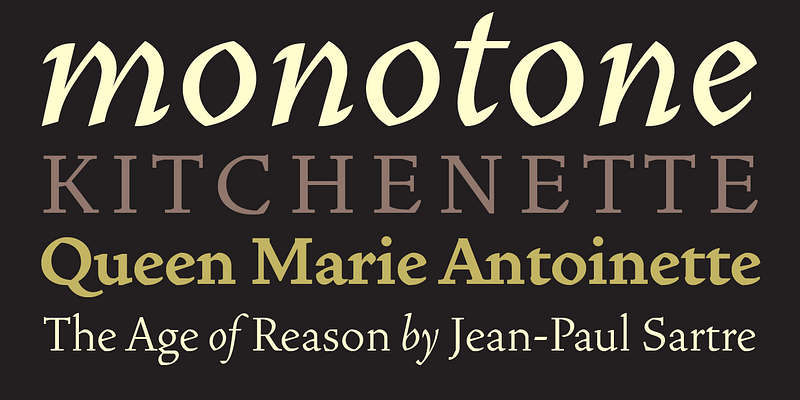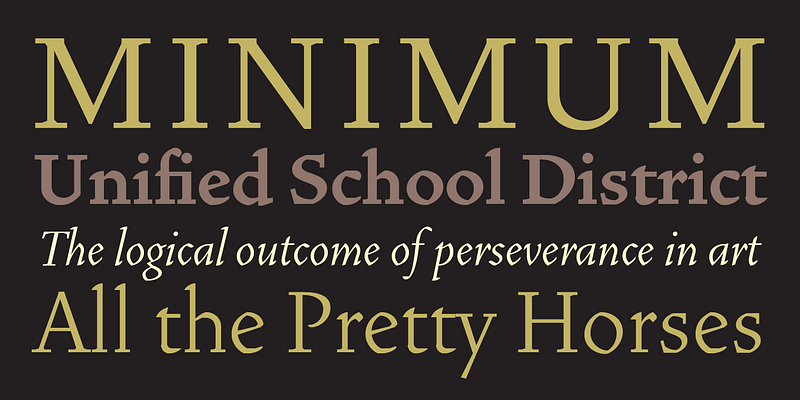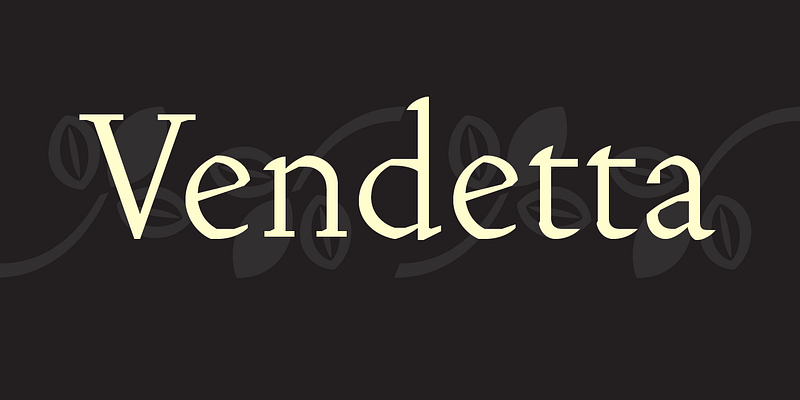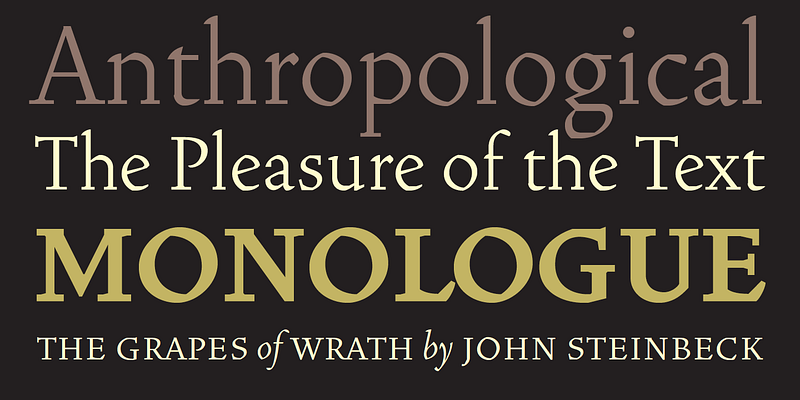
Die berühmte römische Schrift, die Nicolas Jenson in Venedig schnitt und 1470 für den Druck des Traktats „De Evangelica Praeparatione, Eusebius“, verwendete, wird in der Regel als bahnbrechender und endgültiger Vertreter einer Klasse von Schriften bezeichnet, die als „Venetian Old Style“ (Altvenezianischer Stil) bekannt ist. Man geht davon aus, dass der Schrifttyp „Jenson“ das Hauptmodell für die unmittelbar folgenden Schriftarten war. Nachfolgende venezianische Schrifttypen im alten Stil aus dem 15. Jahrhundert, die von anderen Stanzern in Venedig und anderswo in Italien hergestellt wurden, sind ebenfalls eine nähere Betrachtung wert, wurden aber von Schriftgestaltern des 20. Jahrhunderts weitgehend vernachlässigt.
Downers Faszination für diese historischen Schriften begann in den 1970er Jahren und führte schließlich zur Gestaltung seiner ersten Textschrift, Iowan Old Style (Bitstream, 1991). Irgendwann in den frühen 1990er Jahren begann er, Buchstaben für eine andere venezianische Schrift zu kritzeln. Die Buchstaben wurden aus Teilen von Kreisen und Quadraten zusammengesetzt. Das n, ein standardmäßiges Kleinbuchstaben-Kontrollzeichen in einer Textschrift, kam zuerst. Sein ungewöhnlichstes Merkmal war seine Kopfserife, ein halbierter Quadrant eines Kreises.
Die ersten Buchstaben in Vendetta entstanden aus der Überlegung, wie sich die Formen von Kleinbuchstaben und Großbuchstaben im Hinblick auf klassische Ideale und geometrische Proportionen zueinander verhalten, zwei Spitzenwerte in einer Reihe von künstlerischen Vorstellungen, die während der italienischen Renaissance entstanden sind. Solche Ideen sind interessant zu erforschen, aber im Bereich des Schriftdesigns führen sie oft in Sackgassen. Es ist zum Beispiel allgemein anerkannt, dass die reine Geometrie als strenger Ansatz für das Schriftdesign Grenzen hat. Kein römisches Alphabet, das nur auf Kreis und Quadrat basiert, war jemals ideal für das kontinuierliche Lesen.
Im Laufe der Entwicklung seiner Schriftart für Text musste Downer unzählige Kompromisse eingehen. Jede Änderung führte zu einer weiteren Abweichung von seinem ursprünglichen Schema und gab jeder Schrift eine leicht andere Richtung. So blieben beispielsweise nicht alle Bögen radial, und außerdem wurden sie so gestaltet, dass sie von Schrift zu Schrift variierten. Diese Vielfalt trug zur Individualität der einzelnen Stile bei. Die Zähler vieler Buchstaben werden durch sich kreuzende Bögen oder abgewinkelte Facetten beschrieben, und die Köpfe sind nicht rund. In den Großbuchstaben wurden praktisch überall dort, wo Stiele und Serifen zusammentreffen, eckige Klammern verwendet, um die Strenge der Buchstaben zu betonen. Als Ergebnis all seiner Basteleien erhielt die gesamte Familie eine Art reiche, vertraute Grobheit – ähnlich wie die römischen Schriften des späten 15. Jahrhunderts.
Es ist wirklich schade, dass erst im 20. Jahrhundert eine Wiederbelebung dieser schönen Schriften in der englischen Sprache Einzug gehalten hat. Vier Jahrhunderte lang (ca. 1500 - ca. 1900) waren venezianische Schriftarten im alten Stil in keiner lebenden Sprache beliebt. Seitdem kehren die Neuinterpretationen der frühen italienischen Drucktypen mit großer Wucht zurück.
Ein großer Teil des Charakters von Vendetta beruht auf einer Synthese aus alten und neuen Ideen. Merkmale des römischen Schriftdesigns aus der Zeit der Inkunabeln werden mit zeitgenössischen Überlegungen zur optimalen Darstellung von Buchstabenformen auf Computerbildschirmen kombiniert. Vendetta ist also kein historisches Revival. Sie ist vielmehr eine indirekte, aber persönliche digitale Hommage an die römischen Schriften der Stempelschneider, deren Arbeit durch das Vorbild von Jenson aus dem Jahr 1470 beeinflusst wurde.